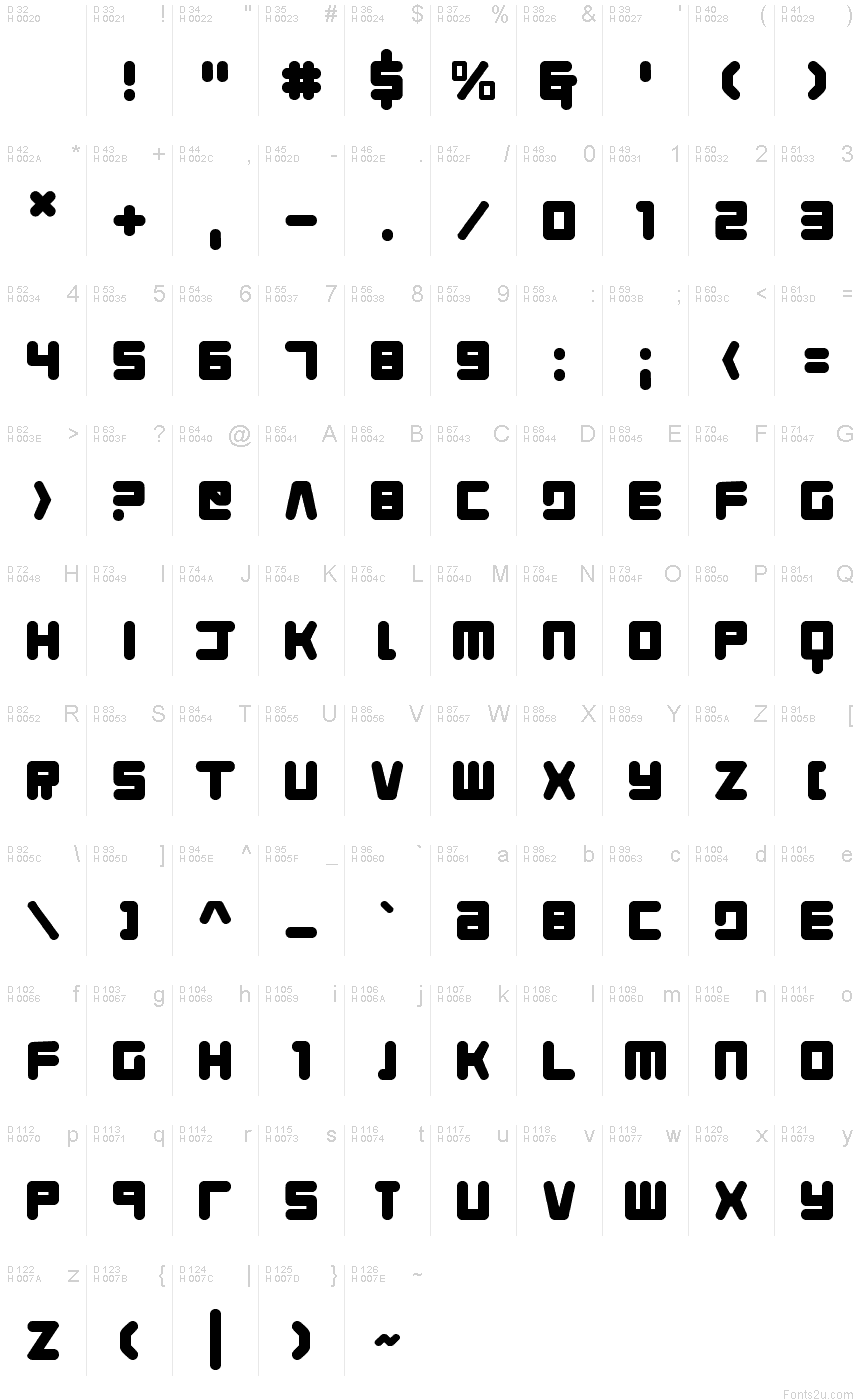
Young Techs ist eine kostenlose Techno-Displayschrift, die 2008 von Iconian Fonts entworfen wurde und auf kräftigen, modularen Strichen basiert. Breite Rundungen und eckige Binnenräume verleihen den Buchstaben das Aussehen gegossener elektronischer Bauteile. Die kompakten Formen zeichnen sich durch eine gleichmäßige, maschinell anmutende Strichstärke aus.
Sie kann einen Titel wie ein Element einer Benutzeroberfläche wirken lassen und eignet sich daher hervorragend für Spielegrafiken und Artworks im Bereich elektronischer Musik. Die abgerundete Geometrie passt zudem zu Technologie-Brandings und futuristischen Eventplakaten, insbesondere wenn ein klarer Industriestil gefragt ist. In solchen Projekten können ihre bauteilartigen Formen an Leiterbahnen, Bedienfelder und vereinfachte Geräteillustrationen erinnern.
Young Techs